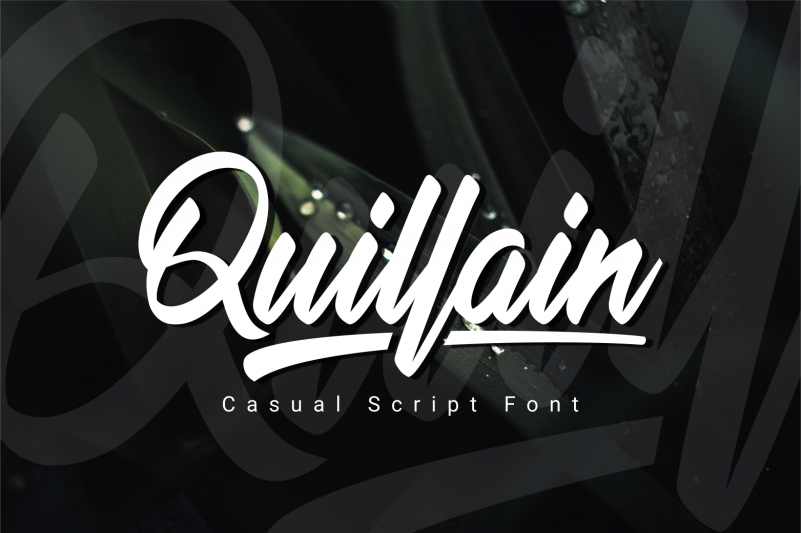
Quillain Script Font – Download Grátis
A fonte Quillain Script é uma escolha perfeita para quem procura uma letra script bold e elegante com uma aparência fresca e versátil. Desenvolvida por nurfdesigns, esta fonte bruta está repleta de recursos que a tornam fácil de usar e altamente adaptável para diversos projetos criativos. A Quillain Script é perfeita para tarefas como criação de logotipos, publicações de citações impressas, convites, cartões, embalagens de produtos, cabeçalhos, logomarcas, papelaria, outdoors, design de roupas e etiquetas. Além disso, a fonte oferece suporte multilinguístico e apresenta várias variações em cada caractere, incluindo recursos OpenType (alternativas e ligações) para maior flexibilidade gráfica. A Quillain Script é uma escolha perfeita para designers que desejam dar um toque diferenciado a seus projetos.